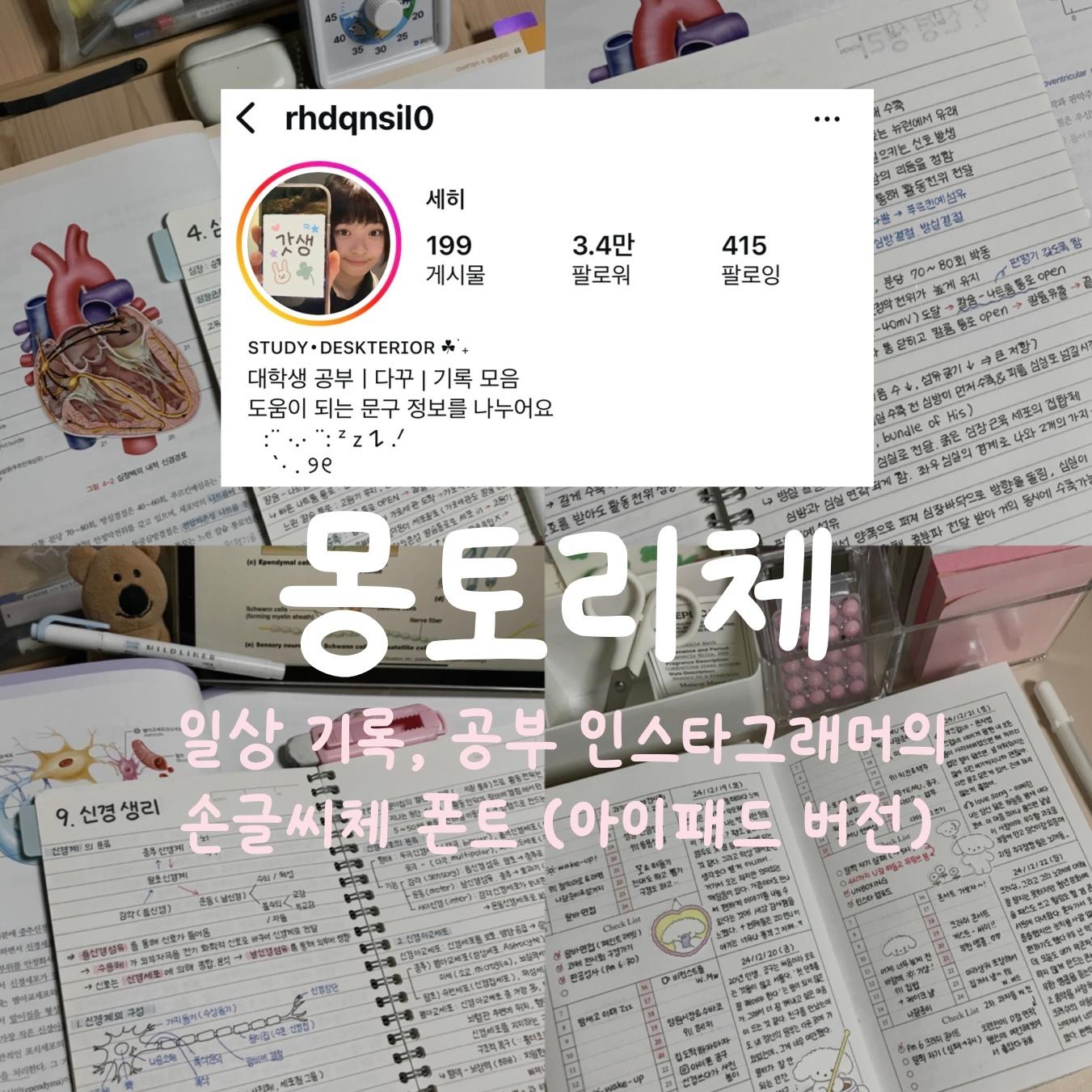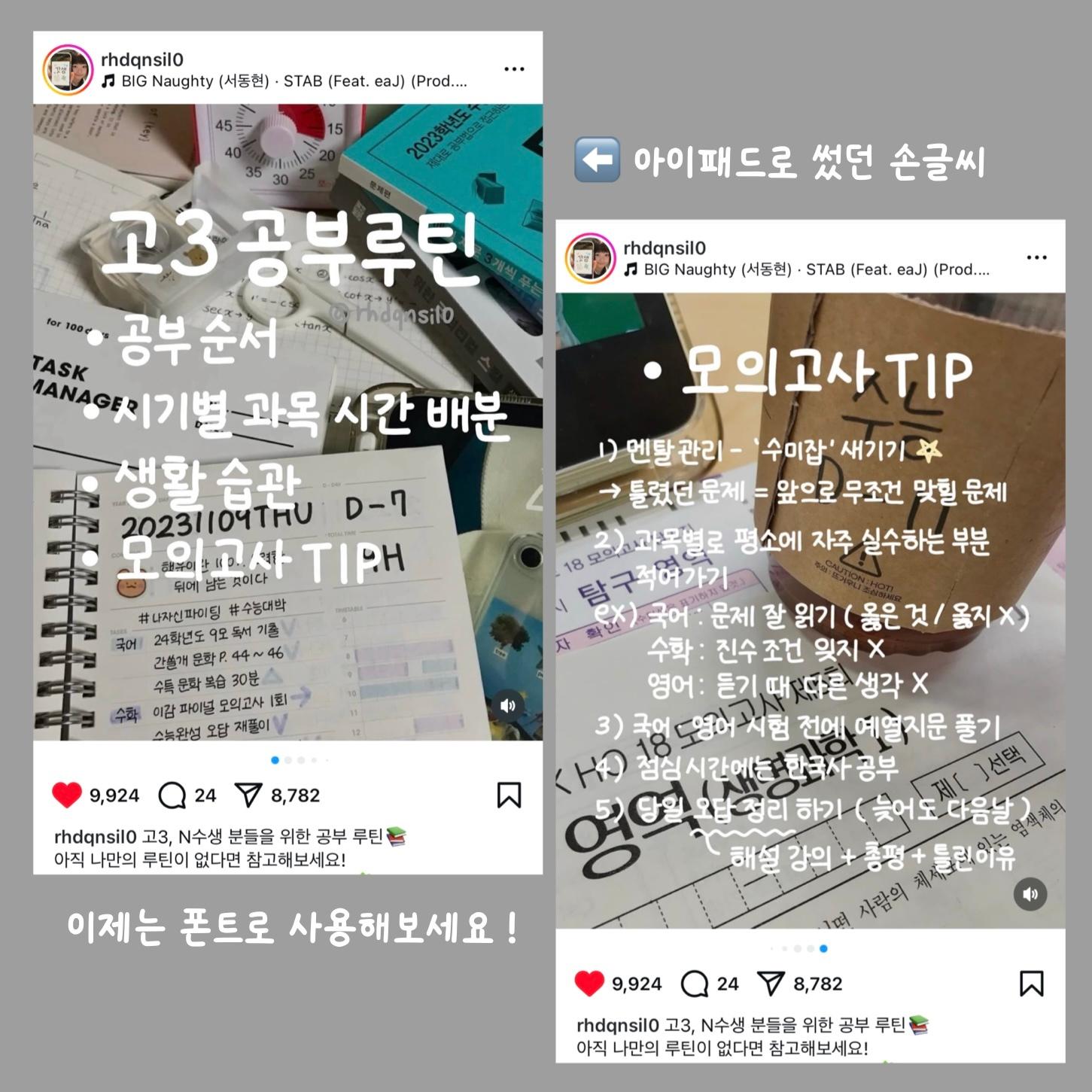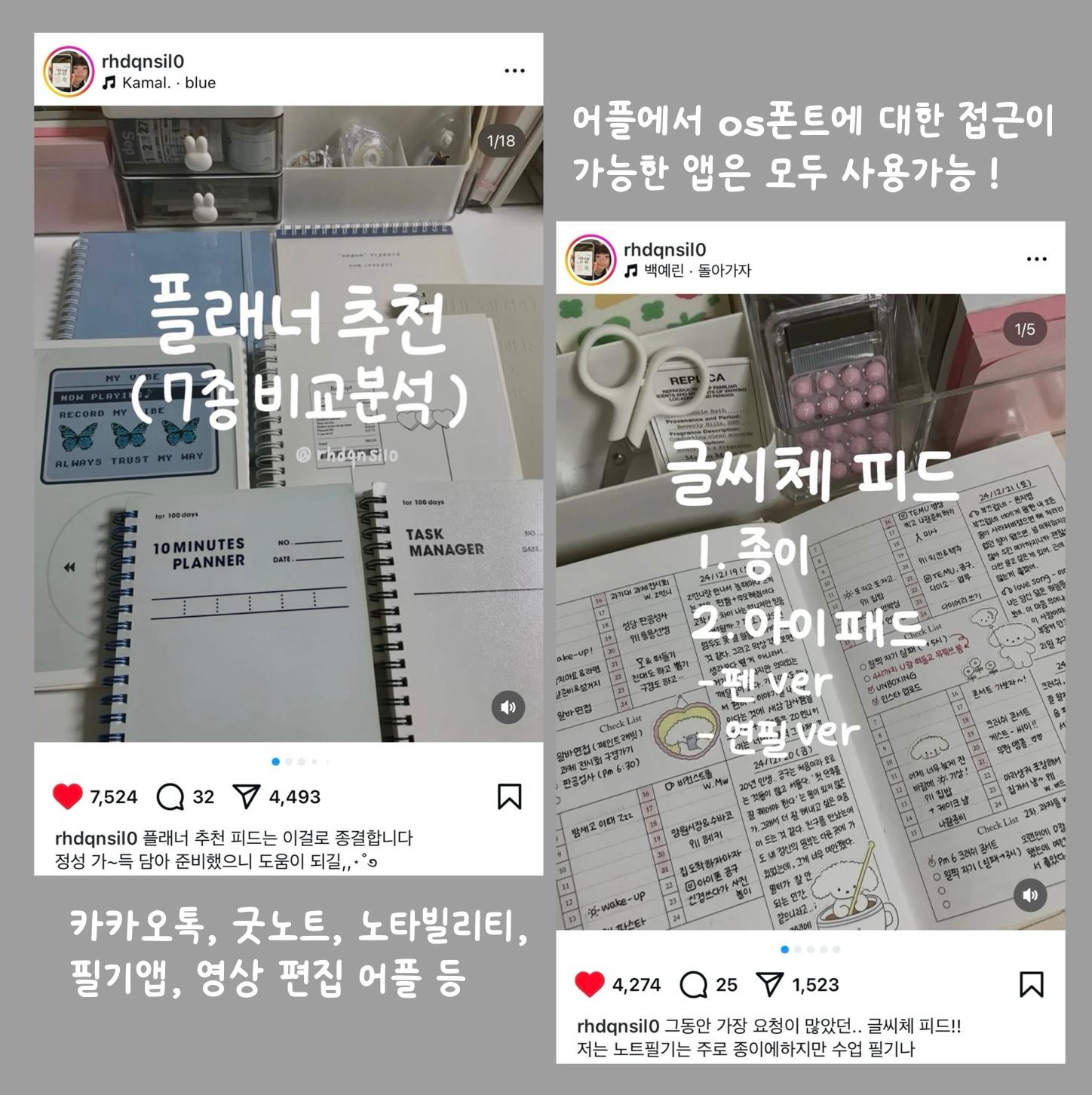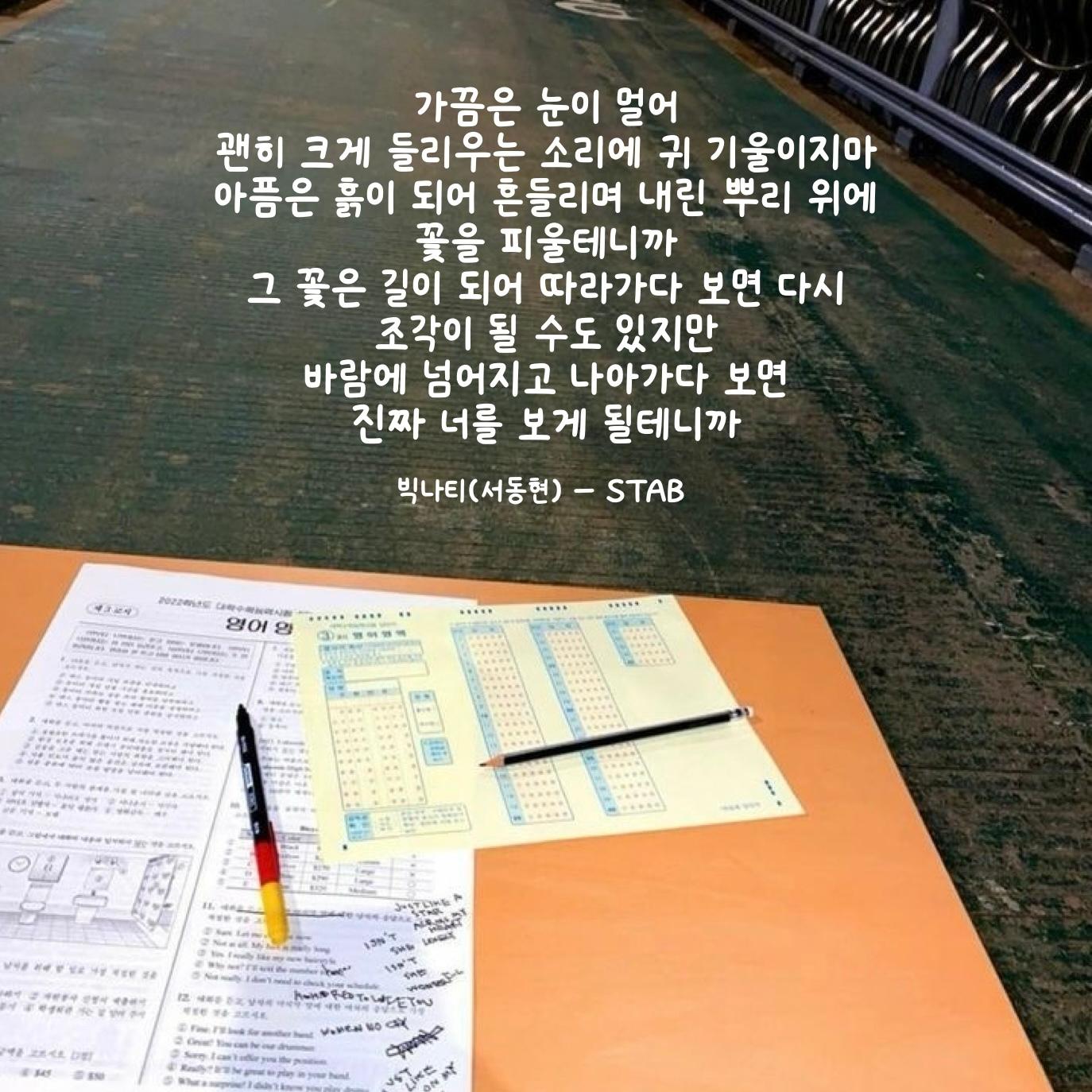
그리운 몽토리체
Griun Mongtori
그리운 몽토리체 소개
그리운 몽토리체(Griun Mongtori)는 동글동글하면서도 반듯한 매력이 돋보이는 폰트입니다. 제 글씨를 보면 "도토리가 떠오른다"는 의견과 "몽글몽글한 느낌이 묻어난다"는 의견이 많아서, 몽토리라는 이름을 붙이게 되었어요. 저는 초등학생 때부터 글씨 예쁘다는 칭찬을 자주 들었는데요. 대학생이 된 지금은 아이패드로 필기하는 일이 더 많아졌고, 그래서 아이패드에 담긴 저의 손글씨를 담아 폰트로 제작했습니다. 몽토리체는 적당한 두께감 덕분에 영상 자막으로 활용하면 가독성이 뛰어나고, 일기장이나 메모, 포스터 등에 사용하면 친근하면서도 깔끔한 인상을 남길 수 있습니다. 자꾸만 보고 싶어지는 글씨, 몽토리체와 함께하세요.